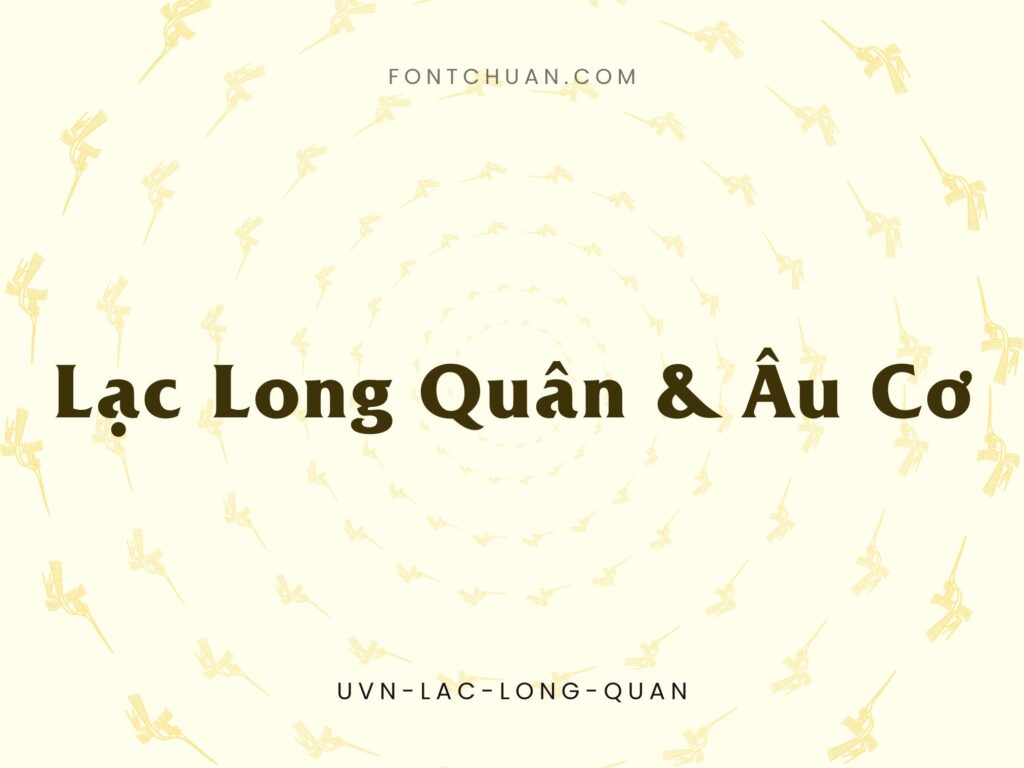
Font UVN Lac Long Quan Việt Hóa
UVN Lạc Long Quân là bộ font mang âm hưởng sử thi và huyền thoại dân gian Việt Nam, gợi nhớ đến truyền thuyết về cha rồng mẹ tiên. Với cấu trúc chữ vững chãi, đường nét dày khỏe và kiểu dáng uy nghi, font này phù hợp cho các thiết kế mang tính truyền thống, văn hóa hoặc cổ điển. Font này chỉ được sưu tầm và đăng bởi thành viên của Font Chuẩn, như một phần nỗ lực bảo tồn và lan tỏa tinh thần dân tộc trong các sản phẩm thiết kế đương đại.
Thiết kế của UVN Lạc Long Quân mang đậm nét Việt với kiểu chữ chắc chắn, các đường nét cứng cáp và chi tiết gợi liên tưởng đến văn hóa Đông Sơn, phù hợp với các dự án truyền thông văn hóa, lịch sử, giáo dục và sự kiện dân gian. Font lý tưởng để sử dụng trong tiêu đề, poster, sách giáo khoa, ấn phẩm truyền thống hoặc lễ hội cổ truyền. Các ngành nghề phù hợp gồm giáo dục, quảng cáo, bất động sản và công nghệ. Sự kiện nên dùng gồm Tết, lễ hội, Trung thu và ngày Nhà giáo.